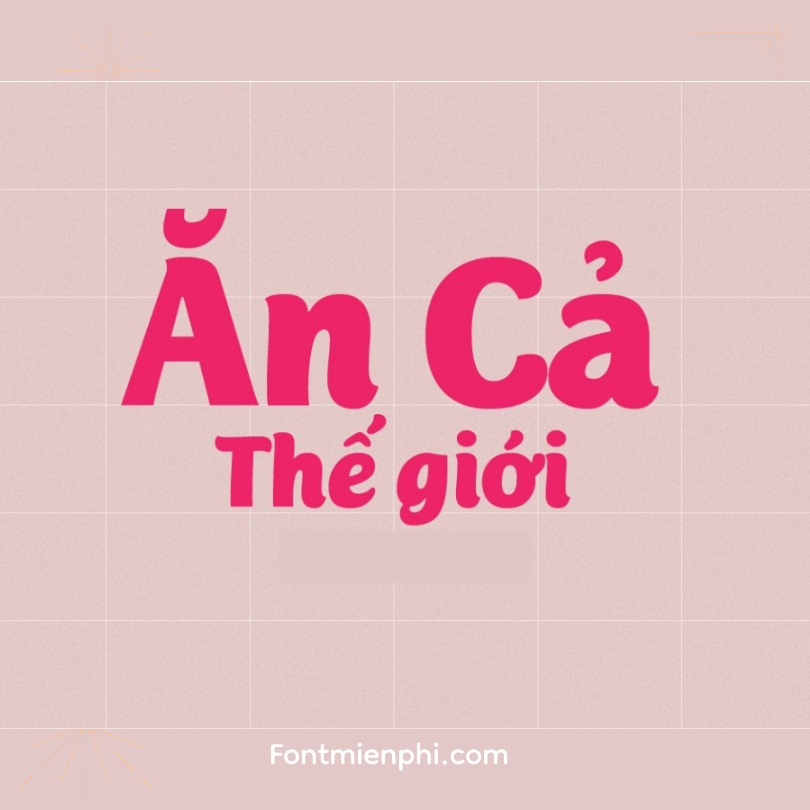
Việt hóa font iCiel Mijas , Ultra
Giới thiệu về bộ Việt hóa font iCiel Mijas , Ultra
Trong thế giới thiết kế đồ họa chuyên nghiệp, việc lựa chọn một Font Miễn Phí chất lượng luôn là ưu tiên hàng đầu của các bạn học sinh và sinh viên. Đặc biệt, bộ Việt hóa font iCiel Mijas , Ultra nổi bật như một lựa chọn hoàn hảo cho những ai yêu thích phong cách mạnh mẽ nhưng không kém phần uyển chuyển. Đây là hai phiên bản độc đáo thuộc họ font Mijas, được đội ngũ iCiel tinh chỉnh kỹ lưỡng để hỗ trợ đầy đủ bảng mã tiếng Việt, giúp người dùng không còn lo lắng về lỗi hiển thị ký tự hay thiếu dấu khi soạn thảo nội dung.
Đặc điểm nổi bật của iCiel Mijas và Ultra
Mijas mang trong mình hơi hướng của những nét cọ vẽ tay thủ công, tạo cảm giác gần gũi và nghệ thuật. Trong khi đó, phiên bản Ultra được tăng cường độ dày của nét chữ, giúp các tiêu đề trở nên nổi bật và thu hút thị giác ngay lập tức. Khi sử dụng Việt hóa font iCiel Mijas , Ultra, bạn có thể dễ dàng áp dụng vào các bài thuyết trình, làm bìa báo tường hoặc thiết kế poster sự kiện trường học. Cấu trúc chữ được thiết kế cân đối, giúp các văn bản dài vẫn giữ được sự rõ ràng và dễ đọc trên cả thiết bị di động lẫn bản in truyền thống.
Cách ứng dụng Việt hóa font iCiel Mijas , Ultra hiệu quả
Để tận dụng tối đa vẻ đẹp của bộ font này, bạn nên kết hợp chúng với các tông màu tương phản cao. Chẳng hạn, chữ màu trắng trên nền ảnh tối sẽ làm nổi bật các đường nét tinh tế của Mijas Ultra. Đối với các bạn học sinh đang làm dự án sáng tạo, việc cài đặt rất đơn giản, chỉ cần tải về và sao chép vào thư mục font của máy tính. Hy vọng bộ Việt hóa font iCiel Mijas , Ultra sẽ là nguồn cảm hứng mới cho các tác phẩm của bạn. Nếu bạn đang tìm kiếm thêm tài nguyên, hãy truy cập ngay Font Miễn Phí, Font Việt Hóa, Việt hóa font iCiel Mijas , Ultra để cập nhật những xu hướng thiết kế mới nhất hoàn toàn miễn phí.